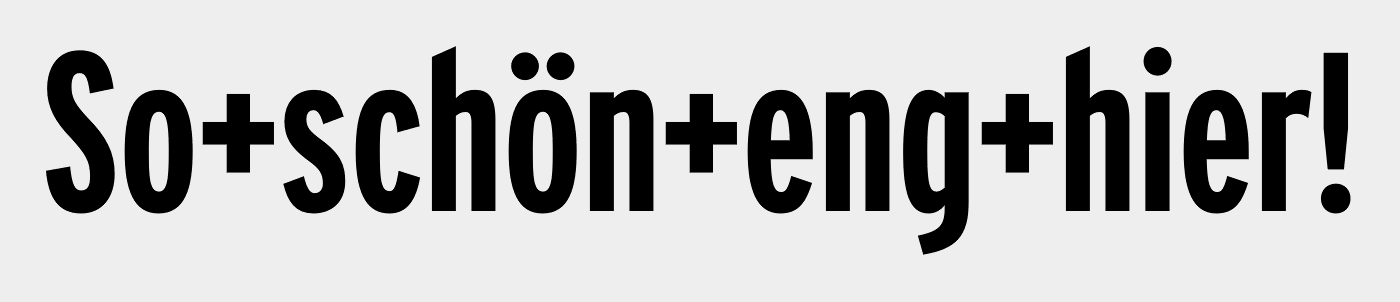
Schmal laufende Schrift gesucht
Suche schmal laufende Schriften, ob Grotesk oder Antiqua spielt noch keine Rolle.
Schmall laufende Schnitte innerhalb einer Schrift oder grundsätzlich schmal laufende Schriften.
Versuch's mal mit der ITC Weidemann Book,
Spontan fallen mir ein:
Corporate ASE Sippe
Franklin/News Gothic etc. Condensed
Univers/Helvetica/AG etc. Condensed
Myriad Condensed
Minion Condensed
Knockout (in ihren schmallen Schnitten)
Fago
Zine Sans/Serif/Slab ?
Frutiger Condensed
Info
Quay
Unit ?
Solex
Die Ehrhardt fällt mir auch noch ein.. auch wenn das vielleicht jetzt - nach 7 Jahren - für dich nicht mehr so relevant sein dürfte ;)